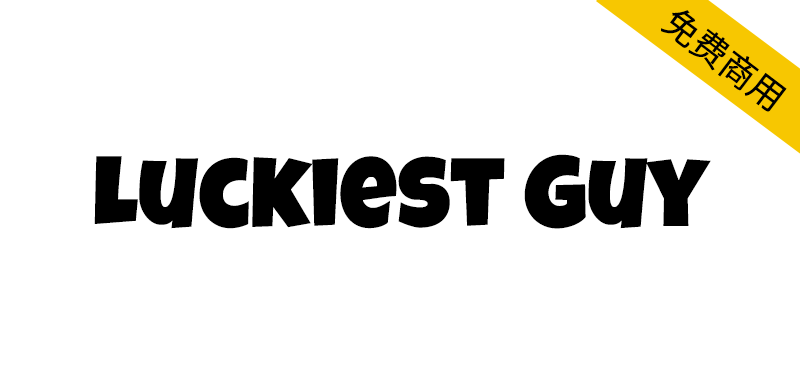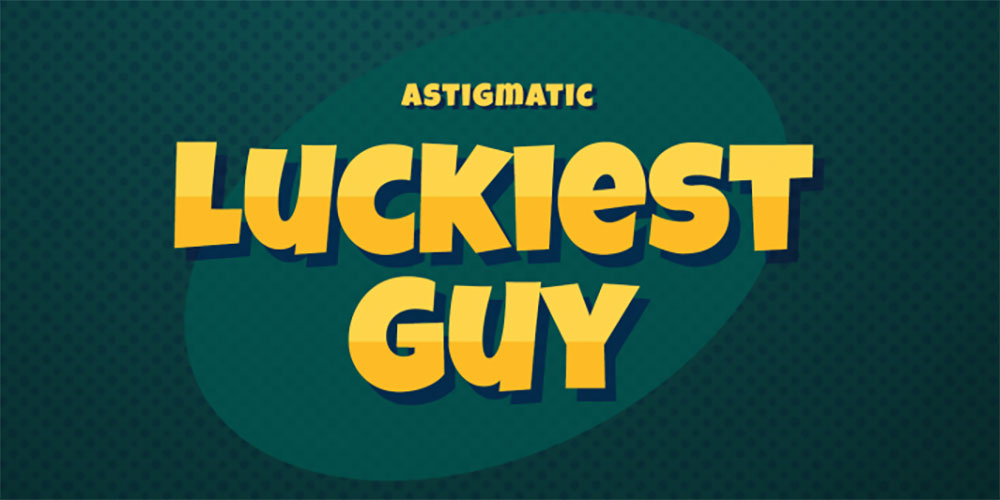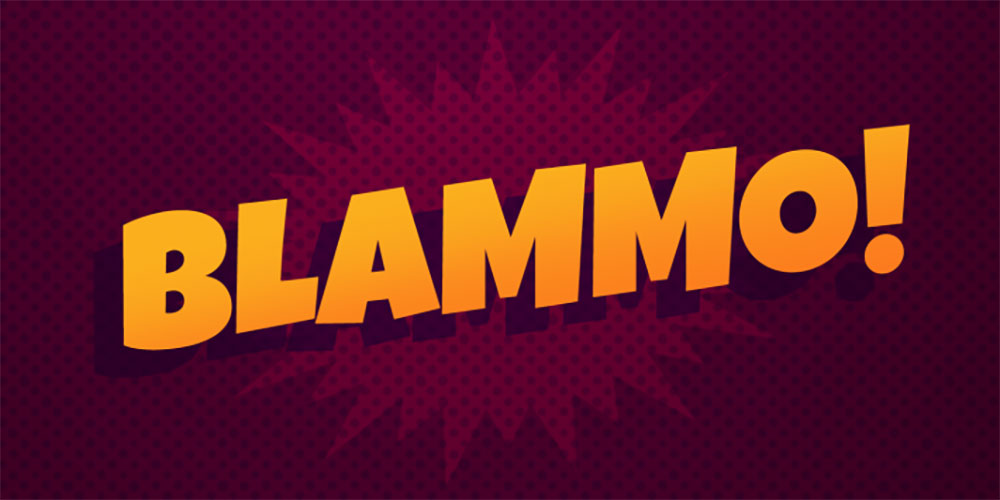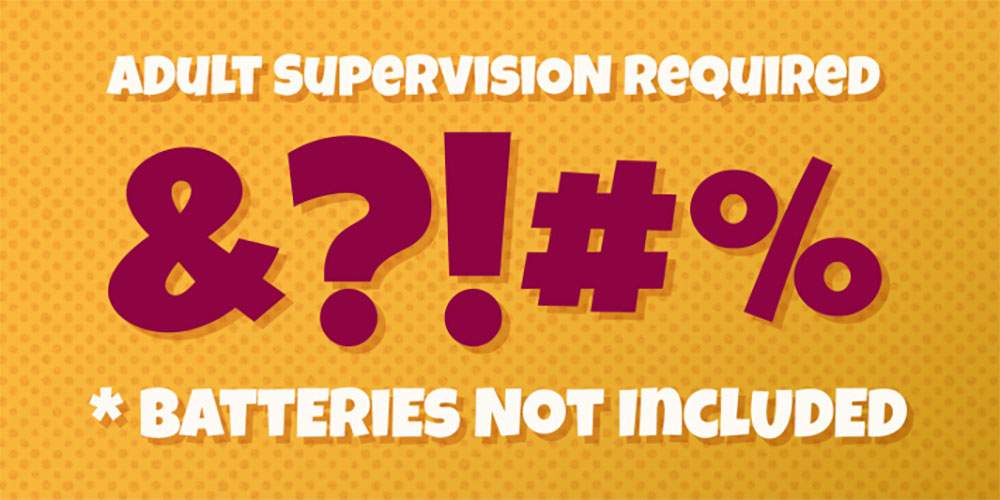
Luckiest Guy 是一款充满活力的无衬线显示字体,由设计师 Astigmatic(AOETI)设计,并通过 Google Fonts 免费发布。这款字体的灵感来自20世纪50年代的美式广告、漫画书和快餐店招牌,以其夸张的粗笔画、圆润的边角和卡通化的风格著称,常被用于需要突出欢乐、轻松、复古或美式漫画感的设计场景。